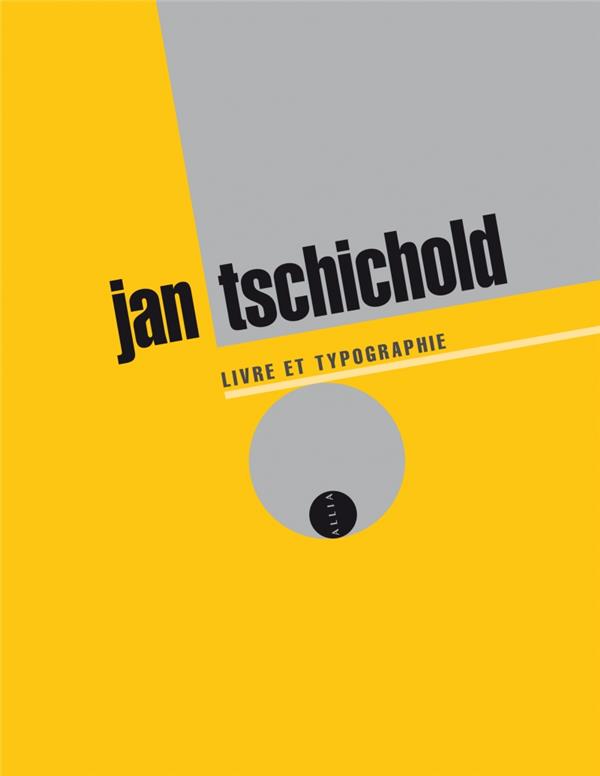
Livre neuf. Livre et typographie. Premier ouvrage de l'auteur à être traduit en français, il offre un choix des essais les plus importants que Jan Tschichold (1902-1974), typographe, dessinateur de caractères, maquettiste, enseignant et écrivain, a fait paraître tout au long de sa carrière. Du rôle de la tradition en matière de typographie à l'emploi des guillemets ou des points de suspension, en passant par les méfaits de la typographie asymétrique, Tschichold livre ici le fruit d'une expérience de plus de cinquante années passées au service du livre.